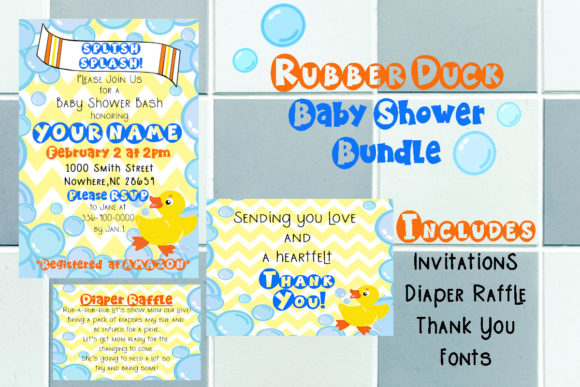
Rubber Duck Baby Shower Bundle and Fonts
Jika Anda mencari aset berkualitas tinggi seperti Rubber Duck Baby Shower Bundle and Fonts, paket premium ini adalah pilihan fantastis untuk proyek kreatif Anda.
Baik Anda membuat produk POD (Print on Demand), undangan pernikahan, atau grafis media sosial, Rubber Duck Baby Shower Bundle and Fonts adalah pilihan yang sangat ideal.